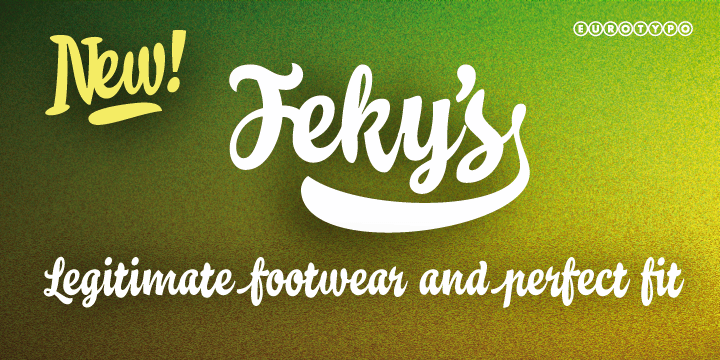
Teja font – Fonte Grátis
Teja font
A fonte Teja é inspirada nas estilos de letra impressas nos rótulos das placas de anúncio enameleadas de ferro. Esses rótulos eram uma característica distintiva dos anos 1800 até o início do século XX, destacando-se nos corredores e estações de trem em mais de mil vilarejos e cidades ao redor do mundo. A influência desta fonte reside no encanto vintage que transmite, com linhas ásperas e formas elegantes. Perfeita para aplicar um toque de sofisticação à sua identidade visual, seja em designs de marca ou projetos gráficos históricos. Inspirada por esse estilo único dos anúncios de ferro enameleado, a Teja oferece uma opção única e memorável para seu próximo projeto.